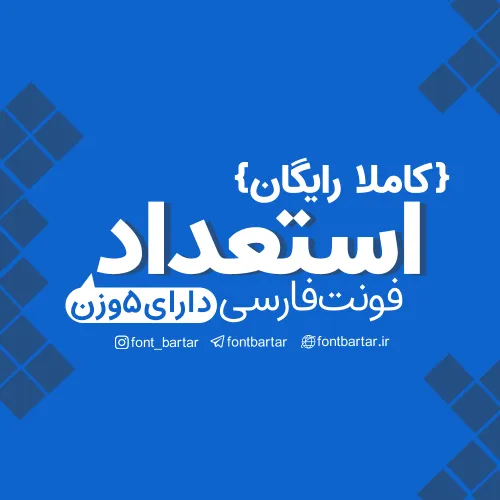
فونت فارسی استعداد
فونت استعداد که یک تایپ فیس سان سریف است در این مطلب از سایت فونت برتر قرار داده شده است. فونت فارسی استعداد برای استفاده در متون طولانی میتواند کارساز باشد.
فونت فارسی استعداد مورد استفاده برای:
• طراحان وب سایت و گرافیست های خلاق می توانند از این مجموعه زیبا فونت در طراحی پروژه های تبلیغاتی و تجاری خود کمک بگیرند.